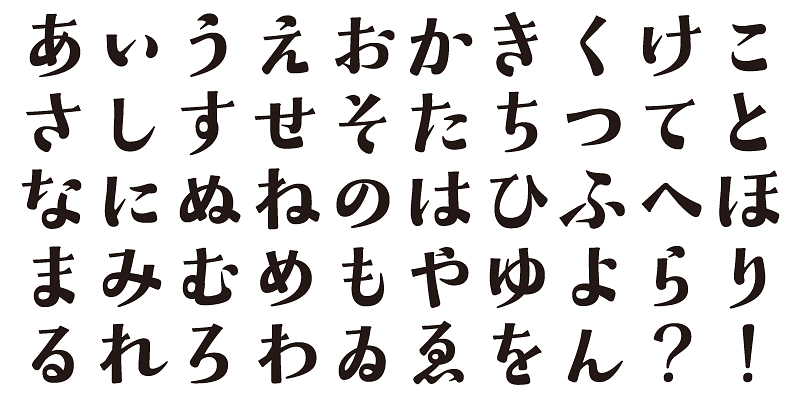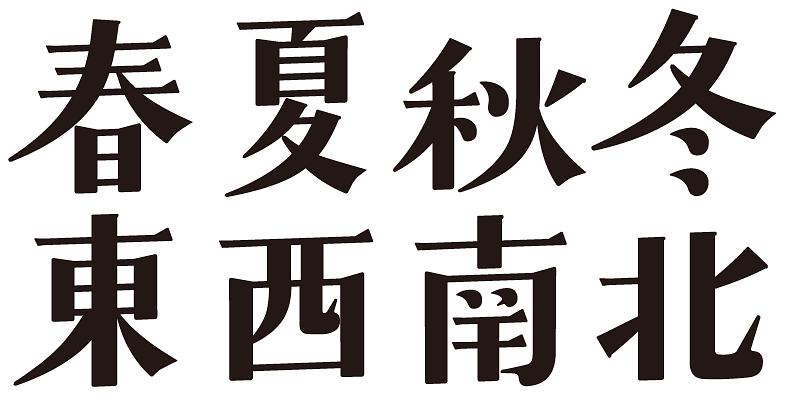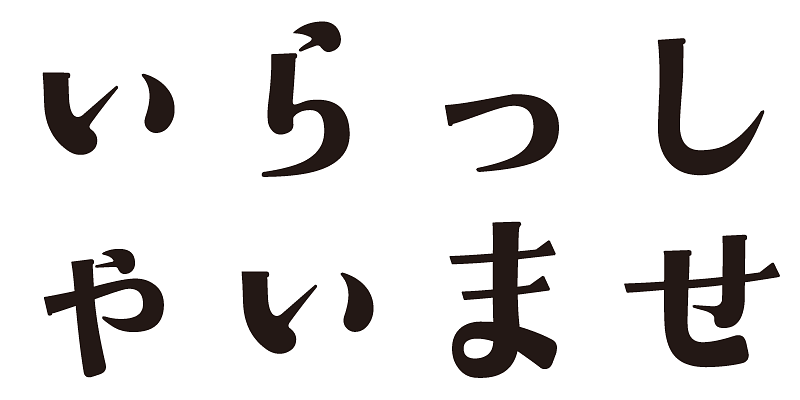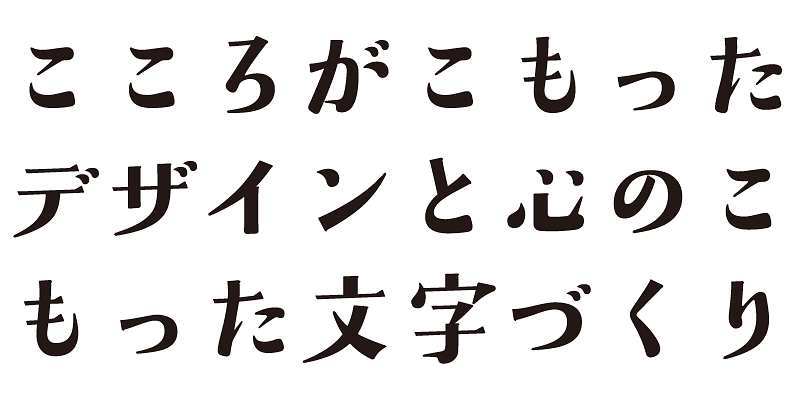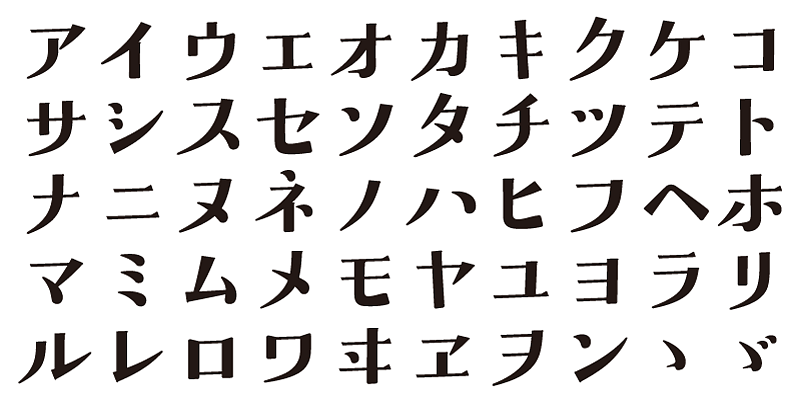
Diese Schrift symbolisiert Meeresrauschen, Wind, Gischt und den würzigen Geruch der Gezeiten. Das Design ist durch die natürliche Brise am Meeresufer inspiriert.
Neben 1.000 Kanji-Zeichen umfasst diese Schrift auch Hiragana-, Katakana-, alphanumerische sowie Interpunktionszeichen.